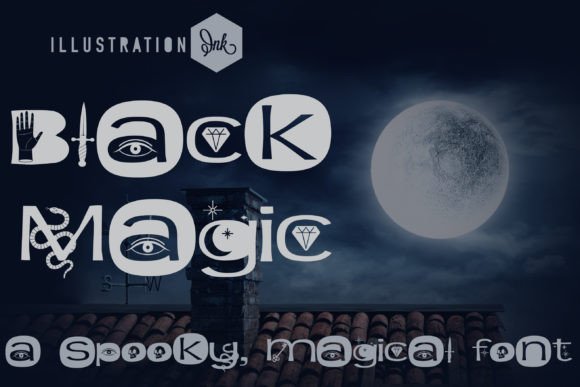
Black Magic
Encontrar los elementos de diseño adecuados puede ser un desafío, pero Black Magic ofrece una colección excepcional que eleva tu trabajo al instante.